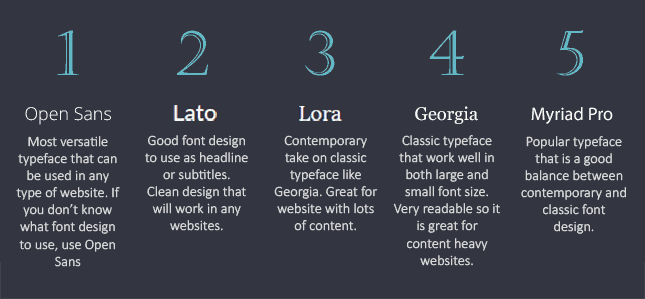
Webデザインに差がつくフォント選びとは?サイトデザインに最適なフォントを考える
ひと口にかっこいいウェブサイトを作ると言っても、膨大な仕事があります。フォントの選択は、サイト作成にあたって山ほどある検討事項のうちの一つです。サイトの内容を書き上げる時や写真を選ぶ時同様、相応しいフォントを慎重に選ぶ必要があります。
サイト作成にあたって、コンテンツの紹介に加え、ソーシャルメディア媒体との連携も確保しなくてはいけません。しかし魅力的なWebデザインを目指す中で、見落とされがちな大事な側面があります。特別にデザインされた、見栄えするフォントを選ぶべきなのです。
一覧して脳裏に残るような書体を選びましょう。相応しいフォントを選ぶことでサイトの質は段違いに良くなります。またフォントを追究すると、ロゴ商標について理解を深めることになるでしょう。
ウェブサイトにとってぴったりのフォントを選ぶなんて難しい!こう思うあなたに、Webサイト上で見栄えするフォント選びのコツをお教えしましょう。
ブランドに合ったフォント選び −方針を明確に−
フォント選びの手順について、まずはブランドと合わせることが第一です。ウェブサイトデザインの流行に合わせることはありません。むしろフォント選びはブランドの発信内容に沿うべきです。
例えば飲料のウェブサイトは、家具と調和した文字を使う必要はありません。顧客のブランドに方針があれば、それに従ったフォントを選びましょう。顧客のブランド方針を把握することは、ブランド戦略を始めとして、顧客のことを効率的に理解することにつながります。
ブランド方針からはあらゆる情報が読み取れます。色やロゴ、そして最も重要な書体です。ブランド方針がある場合、それに忠実なフォント選びをしましょう。
ぶれないフォント選び
常に創造的なウェブデザイナーなら、実験的な試みを思いつくかもしれません。しかしそれはいつも良いとは限りません。人々は名刺やチラシからもブランドの個性を感じ取ります。ウェブサイト上では、一貫したフォントスタイルを採用しましょう。ブランドの認識力向上に繋がります。
一貫したフォントスタイルを採用しないと、ブランドそのものが雑然と取り散らかった印象となります。同一顧客のウェブサイト上では、項目は同じフォントを用いましょう。ただしそれでもなお違うフォントを選ぶのであれば、係累するブランドに用いられているフォントと似ているか確認しましょう。
段階的なフォント選び
“3種類以上のフォントを使わないこと” というWebデザインにおける厳格な決まりごとがあります。配色選びの際に設定する、ベースカラー・メインカラー・アクセントカラーと同様に、どの場所でどのフォントを使うか優先順位をつけます。プライマリーフォント・セカンダリーフォント・アクセントフォントの三種を、内容の重要性に準じて使い分けましょう。
一般にヘッダーは可視性の高いプライマリーフォントを用います。プライマリーフォントは、ロゴに融合するフォントを選ぶことを推奨します。
セカンダリーフォントは判読性の高いフォントを選び、ブログ・記事・説明文・論説など文章部分に用います。プライマリーフォントと比べてセカンダリーフォントは目立ちません。しかし、商品やサービスに関する長い記述を読みやすくします。
アクセントフォントはウェブサイト上の行動喚起要素を強調する際に用います。アクセントフォントはサイトの他の箇所より目立たせる効果を持ちます。特徴的な書体選びをしましょう。
フォントの種類
ここでセリフ・サンセリフ・スクリプト書体の違いを、フォントの分類過程に注目して確認してみましょう。
セリフは印字に向きます。サイトを古風で優雅な雰囲気にし、年配の閲覧者に向いています。サンセリフはセリフに似ていますが、字体の角にある飾り(うろこ)がありません。スマホやPC上で見るのに適しています。ウェブサイト上で最も使われており、若い世代になじみがあります。スクリプト書体とは筆記体のことです。閲覧者の注意を引くのに有効です。可読性に欠けるため、本文よりはタイトルに使われます。
フォントサイズ
フォントの大きさを選ぶことは大変重要です。文字の構成を選んだら、次は大見出し・小見出し・本文の大きさを決めます。サイズとは別に、文字の太さも重要なポイントです。太字にしたり、斜体にしたり、下線を引くべき箇所があるでしょう。ただし過剰な装飾は仕上がりを悪くするので注意しましょう。
流行りを知ろう
流行っている書体を採用しようとすると、サイトの内容と不一致を起こすことがあるでしょう。もし流行っている書体を採用するのなら、大見出しや小見出しにしましょう。セリフやサンセリフと合わせて用いることで、デザインにおける“べし・べからず”の壁を越えることができます。
注意するべきことは、創作にのめり込まないようにということです。最も優先されるべきことは可読性であり、ファンキーな文字でサイトを埋め尽くすことは避けなくてはいけません。
ウェブサイトのフォント選びはブランド次第です。フォントスタイルについて議論することは、ブランドをどのように伝えたいかを見直す機会にもなります。ブランドの個性を反映するフォントは賢く選びましょう。